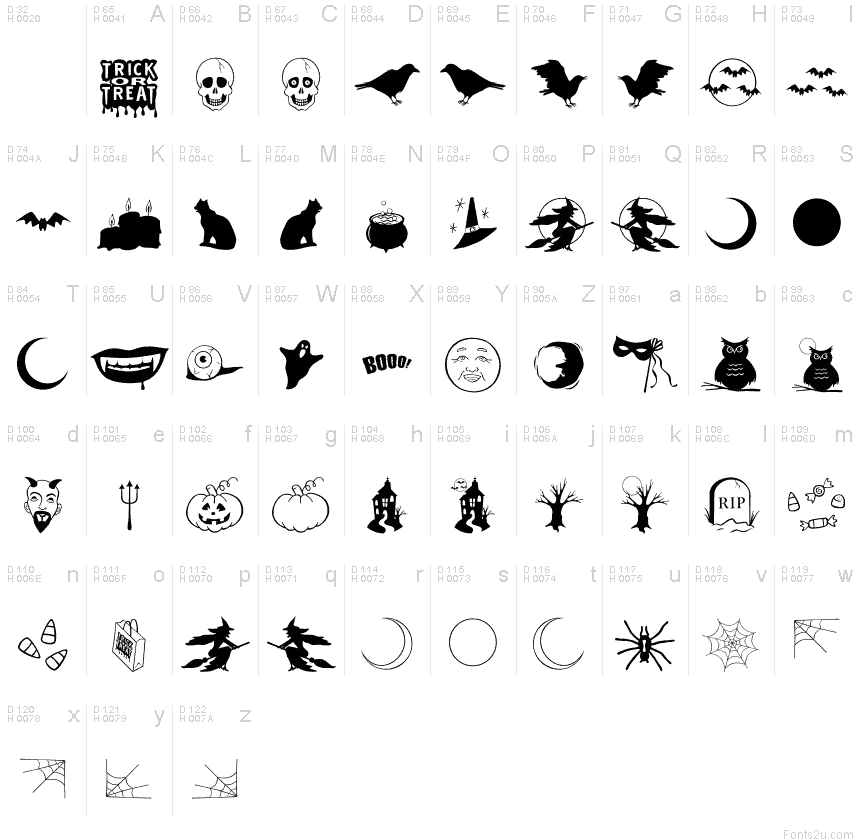
Trick or Treat 2 от BV Fonts — это бесплатный хэллоуинский шрифт-дингбат, созданный на основе выразительных силуэтных иллюстраций. Серпы луны, кривой дом с привидениями, сова и безлистное дерево объединены гладкими сплошными формами и тонкими деталями. Образность отличается прямолинейностью и театральностью.
Приглашения на вечеринки в честь Хэллоуина — его наиболее очевидное применение, причем символы служат готовым сезонным оформлением. Они также подходят для плакатов тематических аттракционов и хоррор-мерчандайза, где знакомые ночные мотивы могут быстро задать нужную атмосферу. Дом с привидениями и сова особенно эффективны в качестве компактных эмблем для графики мероприятий.